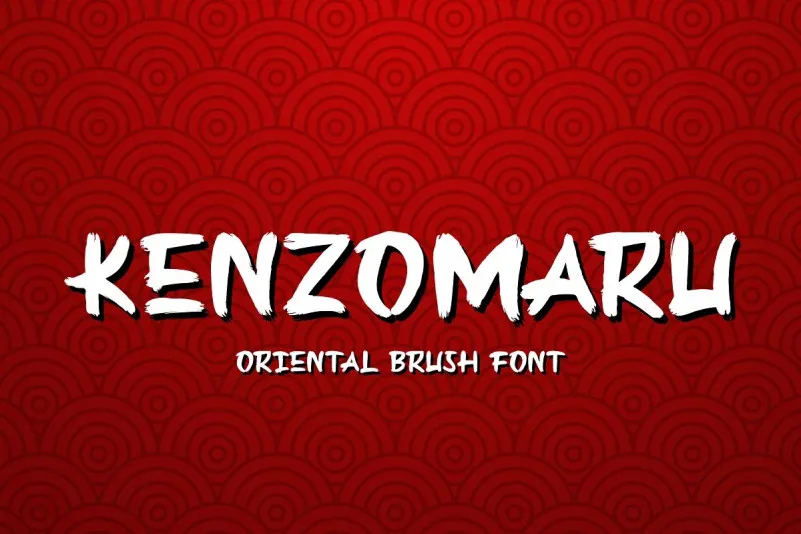
A Kenzomaru Font é uma fonte script all-caps ideal para projetos que exigem estilo sofisticado e personalidade única. Sua aparência robusta e elegante permite manter um tom realista de escrita à mão, dando a você o máximo resultado final possível, mesmo em materiais digitais. Este tipo de letra é perfeitamente adequada para uma variedade de projetos como rótulos, citações, assinaturas, embalagens, cartões de visita e até mesmo campanhas publicitárias. Com sua flexibilidade, a Kenzomaru Font se encaixa em várias aplicações, desde o design de sites e carrosel de fotos até criação de scrapbooking e arte para windows. Para quem deseja explorar ainda mais as possibilidades da estética deste tipo de fonte, é uma excelente opção para a inclusão de elementos fotográficos ou ilustrativos em seus projetos. A Kenzomaru Font, um presente do Almarkha Type, está disponível gratuitamente para uso pessoal e não comercial. Para utilização com fins comerciais, por favor, confira as condições de licenciamento no site referente à fonte.